Как подготовить рукописный шрифт для трафаретной печати на стеклянной бутылке
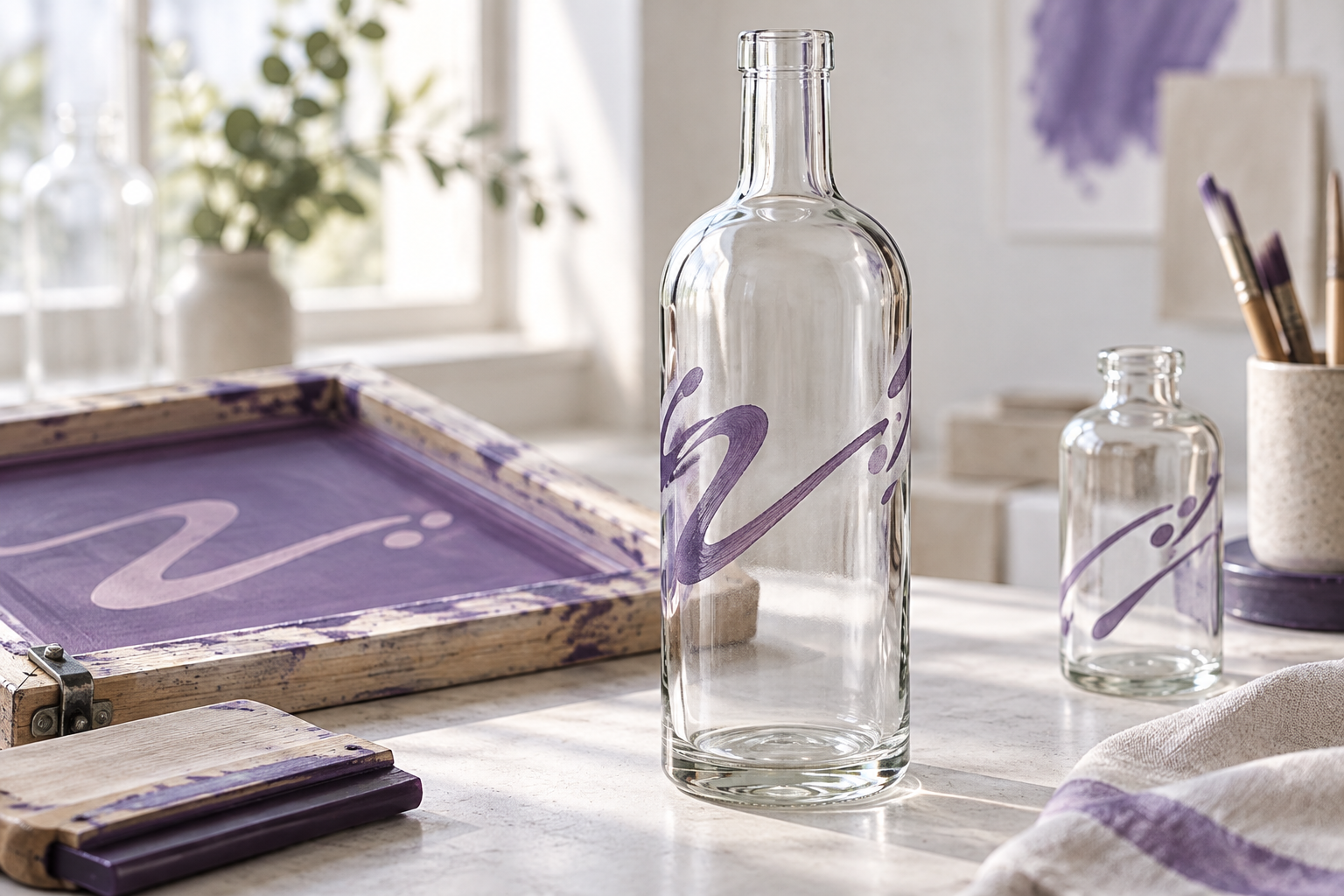
Рукописная надпись на стеклянной бутылке должна одновременно сохранять характер письма, оставаться читаемой на округлой поверхности и выдерживать особенности трафаретной печати. Для этого недостаточно проверить плоский макет: важно оценить контур после оборачивания, решить судьбу тонких просветов и соединений, согласовать краску и сделать пробу на подходящей таре.
Сначала определите, где именно будет жить надпись
До рисования букв выясните у производителя, на какой участок бутылки наносится изображение. У стеклянной тары нет одной универсальной «передней стороны»: корпус может быть цилиндрическим, слегка коническим, иметь плечики, рельеф, шов формы и заметный переход к дну. Даже если надпись печатают только на лицевой панели, зритель видит её под разными углами и часто держит бутылку в руке.
Попросите типографию назвать пригодную для печати зону на чертеже конкретной бутылки и отметить границы, до которых экран или оснастка действительно достают. Попросите также файл развёртки либо габаритный чертёж, если он есть. Не выводите ширину поля только из окружности стекла: часть поверхности может быть скрыта держателем, попадать на криволинейное плечо или требовать отступа от дна и горлышка. Технологическая зона зависит от конкретной линии и приспособления.
Затем решите, должна ли фраза читаться с одной позиции или при повороте бутылки. Для лицевой надписи задайте понятный центр и оставьте запас по бокам. Для круговой фразы заранее обозначьте начало и конец: иначе последняя буква может оказаться в неудобном месте, а стык будет выглядеть случайным. На макете нанесите вспомогательные метки центра, оси и границы видимой зоны, но не включайте их в печатный слой.
Постройте плоскую композицию с учётом кривизны
Обычный макет в редакторе плоский, а бутылка округлая. При взгляде спереди центральная часть воспринимается шире и спокойнее, боковые участки уходят из поля зрения и визуально сжимаются. Если растянуть длинную фразу почти по всей окружности, её начало и конец могут исчезать за боковой касательной. На фотографии фронтальный макет выглядит ровным, а на реальной бутылке композиция кажется чрезмерно широкой.
Начинайте с макета в масштабе 1:1 и контурной схемы бутылки. Разместите слово в центральной зоне, затем проверьте его с фронта, под небольшим левым и правым углом и в перспективе поворота. Если типография может предоставить трёхмерную визуализацию или шаблон оборачивания, используйте его как вспомогательную проверку, но не считайте рендер заменой образца. Блик, цвет стекла и положение источника света способны поменять восприятие контраста.
Для короткого названия часто полезнее уменьшить ширину композиции и оставить боковые поля, чем растягивать отдельные буквы. Если надпись должна охватывать корпус, разбейте её на зрительно понятные фрагменты: главный знак на лицевой стороне, продолжение или вторичную информацию сбоку. Не переносите точку деления механически в середину слова. Если разделение разрушает естественный жест, лучше выбрать другой размер кегля, иной интервал или отдельное начертание для короткой версии.
Проверьте макет с фактической формой стекла: прозрачное и тёмное стекло, высокий цилиндр и бутылка с выраженным плечиком создают разную оптическую картину. Если точной тары пока нет, используйте полноразмерную бумажную полосу, оберните её вокруг близкого по форме образца и отметьте, какие части текста уходят за бок. Это не предсказывает точный печатный результат, зато быстро выявляет слишком широкую строку и неудачное положение стыка.
Сохраните характер почерка, но уберите хрупкие места
Сильная сторона рукописного шрифта — индивидуальный ритм, неодинаковые соединения, живой наклон и переменная толщина. При подготовке к печати не нужно превращать надпись в геометрически ровную гарнитуру. Нужно найти детали, которые на стекле и в выбранном процессе перестанут работать как задумано.
Рассмотрите каждую букву в двух режимах: как чёрный силуэт и как набор внутренних просветов. Тонкая перемычка может потеряться, соседние штрихи — слиться, а маленькое замкнутое отверстие — заполниться краской. Опасны не только тонкие положительные линии (сама краска), но и тонкие выворотки, где краски нет. Печатник подскажет допустимую толщину линий и просветов для конкретных краски, сетки, поверхности и оборудования; универсального безопасного значения для любой бутылки нет.
Особенно внимательно проверьте пары похожих букв, соединения, диакритику и длинные выходные штрихи. У рукописной «а» или «о» важно не потерять внутренний просвет; у букв с пересечением — не закрыть место сочленения; у высокой петли — не спутать её с бликом или царапиной на стекле. Если декоративная линия нужна только для движения, а не для различения знака, её можно упростить или убрать в версии для печати.
Сделайте две копии надписи: исходную и производственную. В производственной версии аккуратно укрепите самые уязвимые линии и откройте тесные просветы, но сохраняйте узнаваемую динамику пера. Не увеличивайте толщину всех штрихов одинаково: это изменит контраст и характер. Исправляйте только те места, где проба показывает реальную потерю, и храните изменения отдельно, чтобы не повредить оригинальный рисунок.
Подготовка рукописной надписи для стеклянной бутылки — это совместная проверка рисунка, окружной композиции и реального печатного процесса. Сохраните выразительность исходного почерка, но принимайте решения о тонких линиях, просветах и цвете по образцу на целевой таре. Если вы создаёте собственный рукописный шрифт, соберите нужные буквы и проверьте их в слове с помощью Fontgenerator, а затем согласуйте производственную версию с типографией.